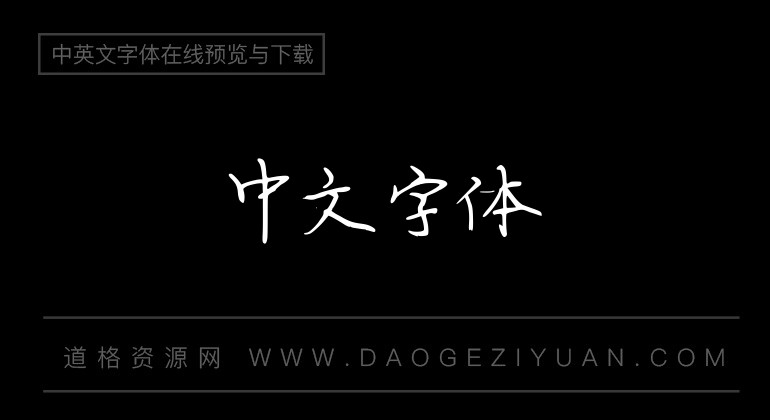
戴锦好字体
戴锦好字体是一款非常优秀的中文字体,它由戴锦好设计制作,是一款汉字字体,具有优美的曲线、清晰的笔画和温暖的气息。字体采用拉丁字母和简体汉字,拥有良好的可读性和可传达性,适用于各种文字排版。字体采用精心设计的技术,使字体具有更好的空间分布,使排版更加美观。此外,字体还采用了抗锯齿技术,使字体更加清晰,更加细腻。戴锦好字体是一款非常细腻、优雅的字体,适用于各种文字排版。
戴锦好字体是一款非常不错的手写艺术字体,具有很好的视觉感,适合于文化类的宣传设计、商业类品牌的广告和产品包装设计以及个性化文字排版等较多场景。